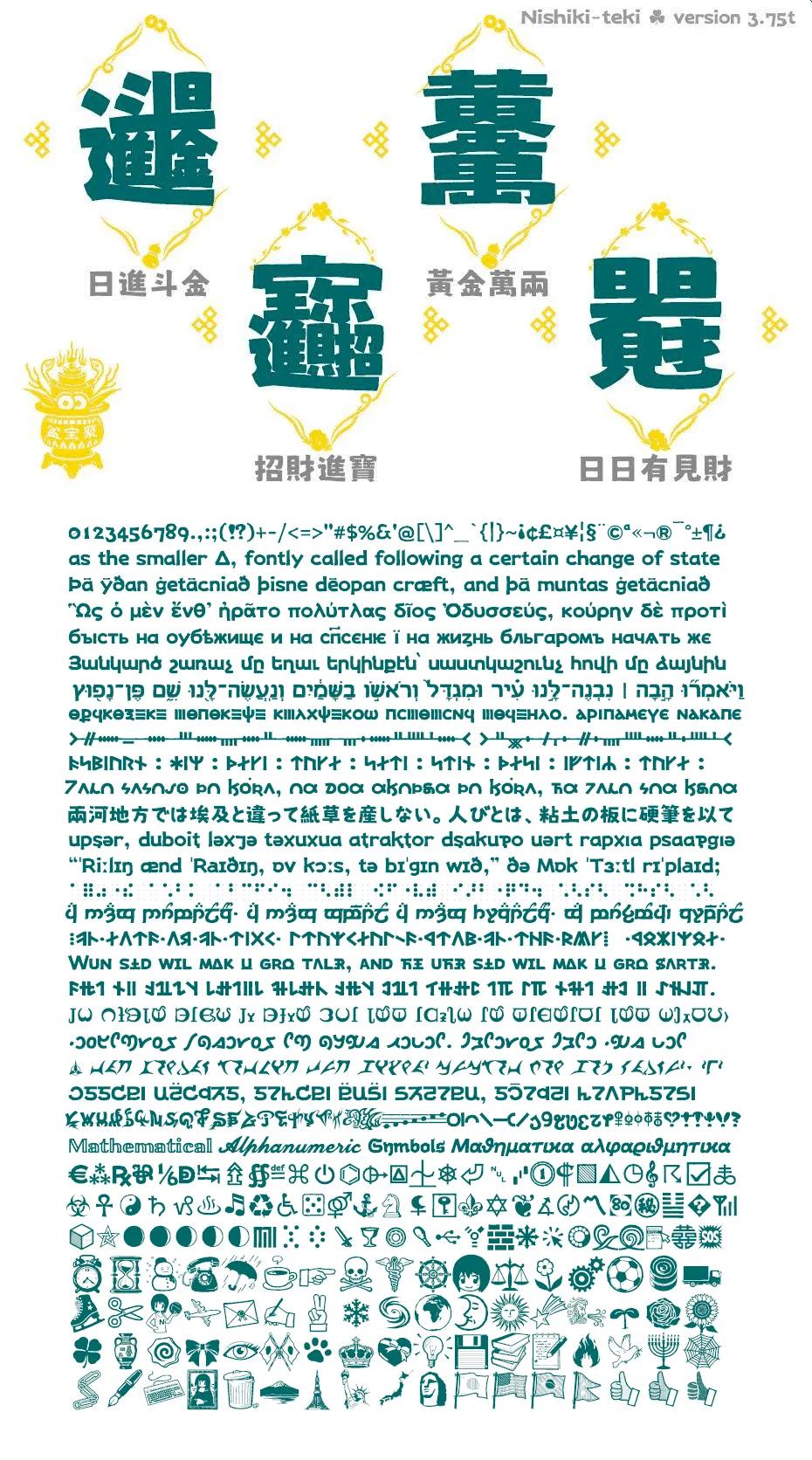
Nishiki-teki是一款可愛的馬克筆手繪風格日系免費商用字體。當前版本包括:拉丁語、希臘語、西里爾語、亞美尼亞語、希伯來語、格魯吉亞語、奧格姆語、北歐古語、科普特語、格拉哥里語,平假名,片假名,注音,漢字,傈僳語,大阪,音標,盲文圖案、一定量的表情符號、各種符號和標點符號等。
注意:Nishiki-teki字體不適合用於簡體字,因為缺字嚴重,適用於繁體和日語,如果需要簡體版,請選擇“貓啃什錦黑”,貓啃什錦黑是專門針對Nishiki-teki字體進行簡體字補充的一款字體。